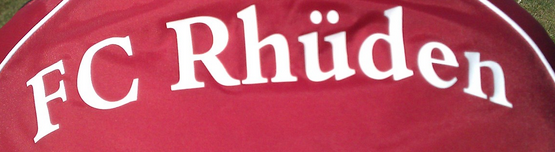
Schriftart gesucht anhand eines fotos
und zwar geht es darum: unser fussballverien möchte sich neue trikots zulegen für einige spieler.
soweit so gut. ABER: da nur einige ausgetauscht werden sollen, muss der schriftzug auf dem rücken natürlich identisch sein. die jungs wollen ja nicht wie die letzten dorfdeppen auf dem platz auflaufen ;)
so, nun stehen wir wie pik 7 da, weil keiner mehr weiss, wo die trikots gedruckt wurden, geschweige denn welche schriftart es ist.
unser verein und ich hoffen wirklich sehr, das es hier jemanden gibt, der uns helfen kann.
und hier folg nun endlich das foto ;)
Ich würde sagen, dass die Adobe Garamond sehr dicht dran ist. Das C ist etwas anders.
... oder die Aldine 401 von Bitstream (evtl. gestaucht, oder das wirkt nur durch die Rundung so)
Handelt es sich hier um das Rhüden bei Seesen, gibt es überhaupt ein anderes?
Die Garamond scheidet aus, das muß die Aldine sein, jedenfalls spricht diese charakteristische Beule rechts am e dafür.
die jungs wollen ja nicht wie die letzten dorfdeppen auf dem platz auflaufen … weil keiner mehr weiss, wo die trikots gedruckt wurden …
...  jedenfalls spricht diese charakteristische Beule rechts am e dafür.
Da war ich mir nicht sicher, ob das an einer Falte liegt. Das C passt aber auf jeden Fall besser ...